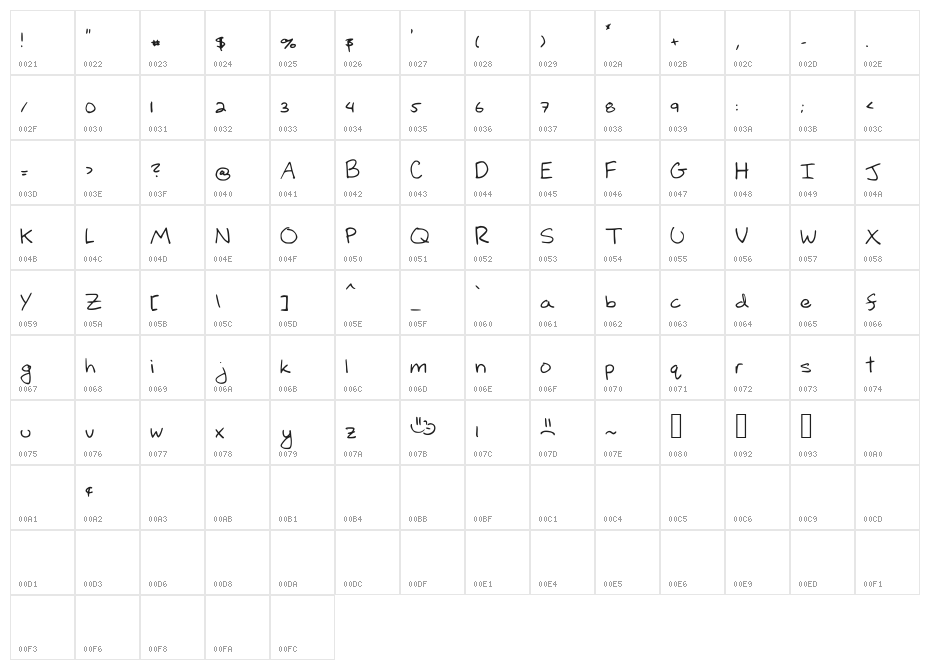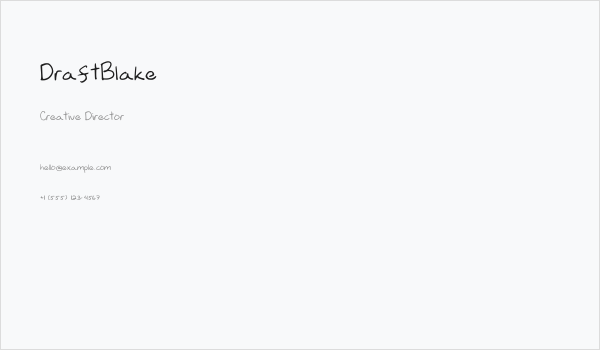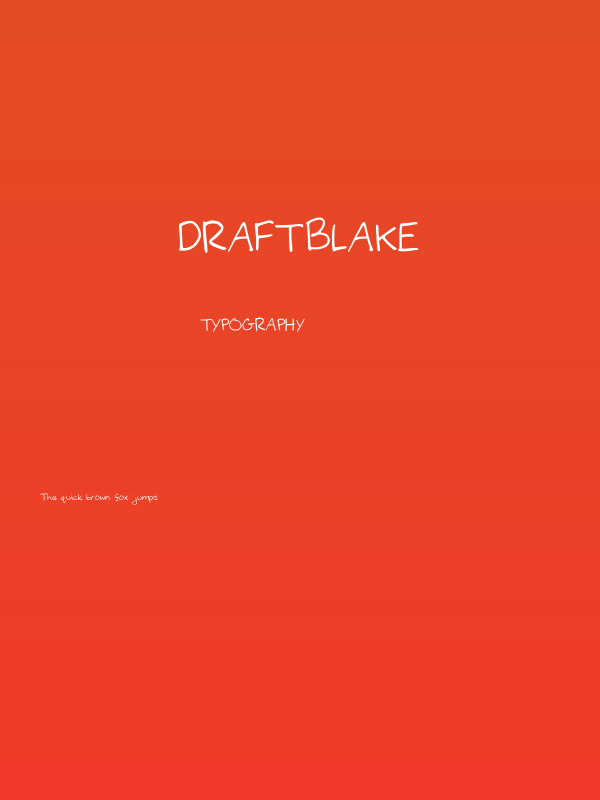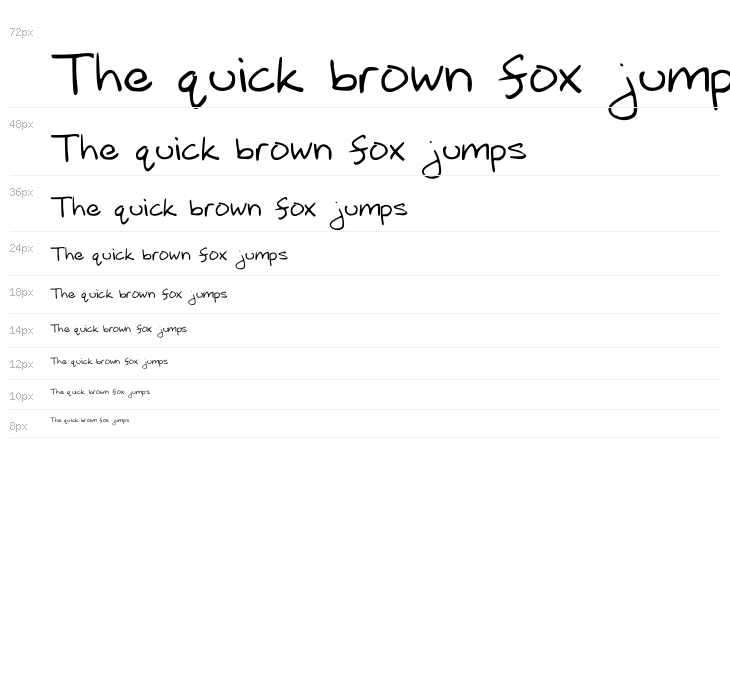
DraftBlake Font
| Gesamtstil | Casual |
| Anwendungsfall | Logos, Headlines, Informal Text |
| Vorgeschlagene Projekte | Ideal for greeting cards, children's books, personal blogs, and informal branding projects. |